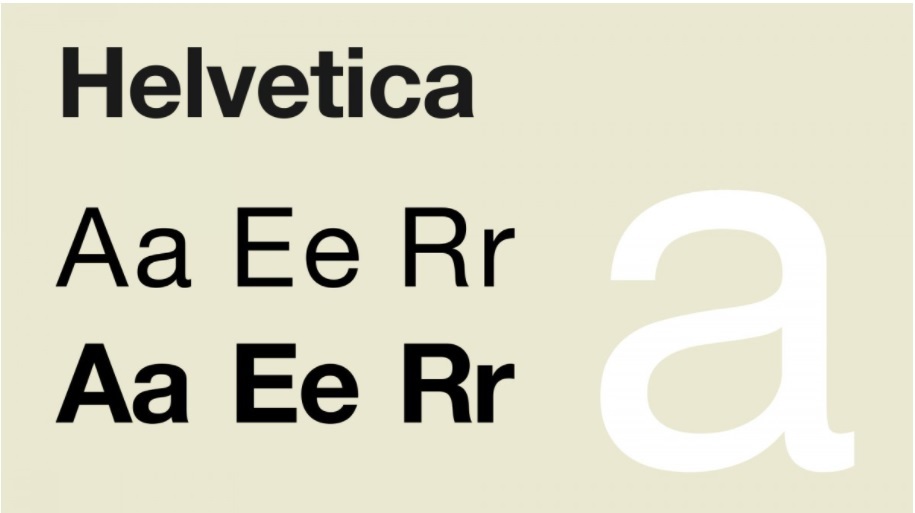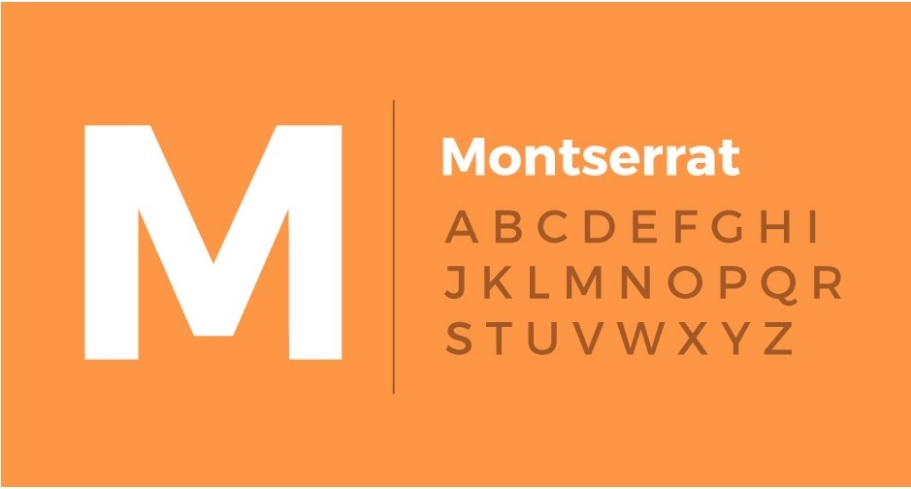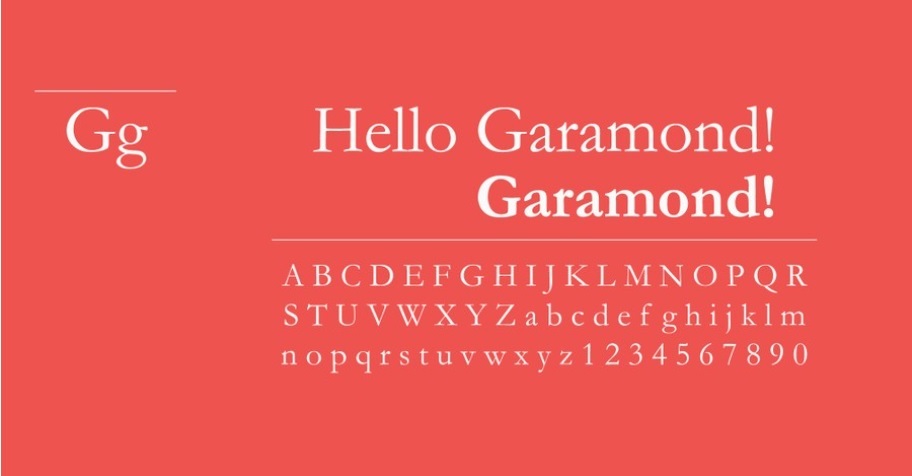
Một số mẫu font chữ đẹp cho bạn tham khảo
1. Font chữ Helvetica
Là font chữ mà được các designer sử dụng thường xuyên nhất bởi kiểu chữ đơn giản, dễ đọc cùng với khả năng truyền tải nội dung thông điệp một cách dễ dàng nhất. Nó là một kiểu chữ hiện đại phù hợp với hầu hết các loại văn bản, các trang báo và kể cả lĩnh vực marketing.
Font chữ Helvetica
2. Font chữ Montserrat
Montserrat là một font chữ thân thiện với người dùng. Được sử dụng nhiều cho việc thiết kế giao diện web và thiết bị di động. Nhưng khả năng biểu thị chữ đậm của nó không được sắc nét khi bạn muốn trình bày một đoạn văn bản dài.
Font chữ Montserrat
3. Font chữ Garamond
Mặc dù đã cho ra mắt rất nhiều phiên bản cải tiến. Nhưng phiên bản được yêu thích nhất lại là bản năm 1989 do Adobe ITC Garamond phát hành. Garamond là một font chữ vô cùng tuyệt vời, thích hợp trên cả sách, báo, tạp chí. Và được những nhà xuất bản, sử dụng rộng rãi nhất chỉ xếp sau Helvetica mà thôi.